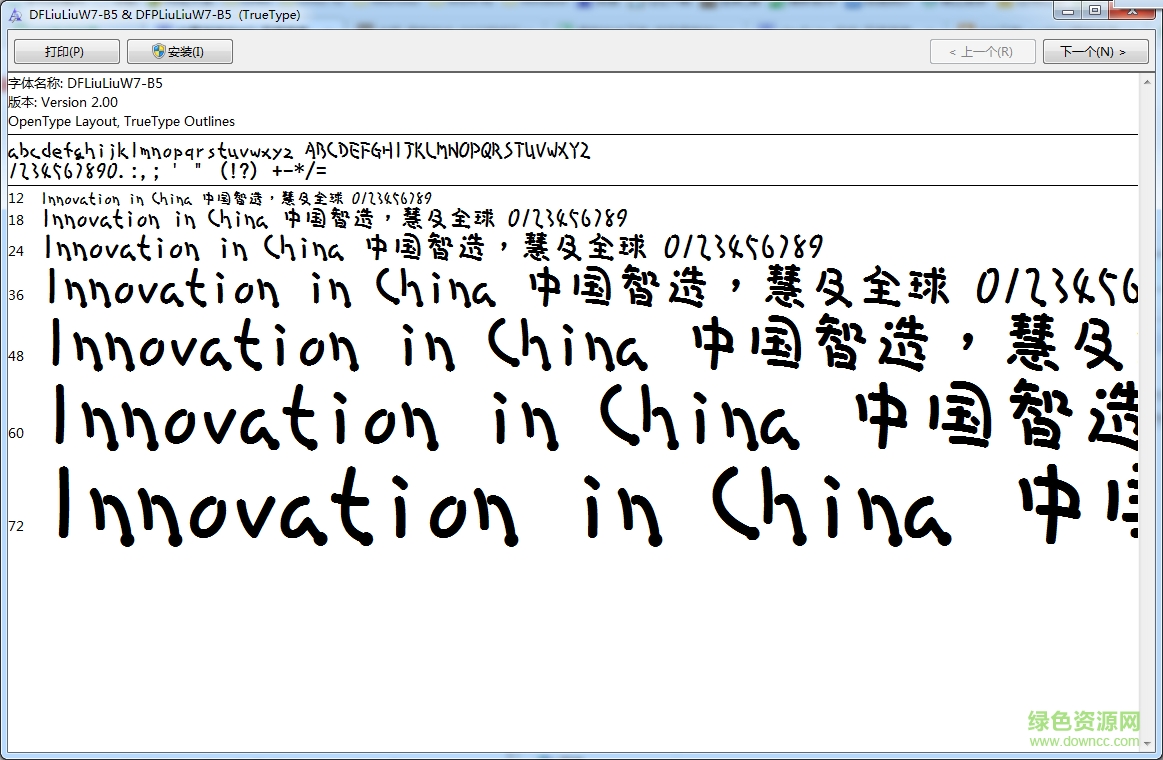
華康溜溜體繁W7
華康溜溜體繁W7是一款獨(dú)具個(gè)性的華康字體類型,字體歪斜圓潤(rùn)可愛(ài),中英文互相轉(zhuǎn)換切換流暢,快速安裝即刻使用。快來(lái)綠色資源網(wǎng)下載體驗(yàn)吧!
華康溜溜體是一款設(shè)計(jì)感非常強(qiáng)的字體,它能夠?yàn)橛脩籼峁┲杏⑽碾p語(yǔ)字體,有喜歡的朋友可以下載學(xué)習(xí)使用~